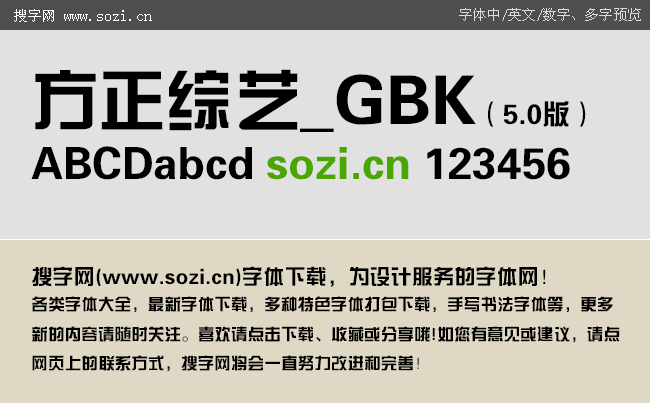
方正綜藝-GBK
搜字網(wǎng)提供一款方正綜藝-GBK下載。綜藝體是黑體的一種變體,也是藝術(shù)字的一種。特點(diǎn)是筆劃更粗,盡量將空間充滿。同時(shí)為了美觀,對拐彎處的處理較為圓潤。GBK碼收錄字體更全,適用于廣告、報(bào)刊等的標(biāo)題及海報(bào)展板等設(shè)計(jì)場合使用。